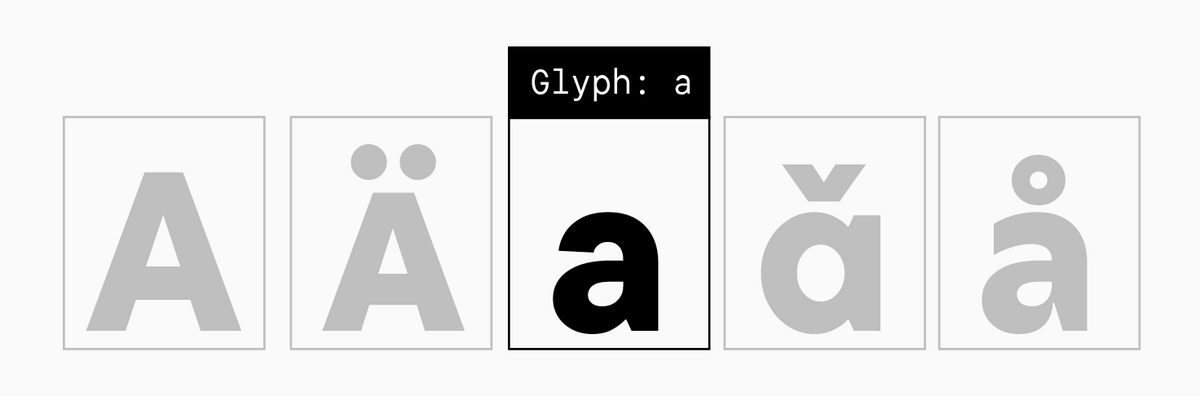
Словарь типографических терминов
Шрифтовой словарь TypeType — это справочник, в котором вы найдете определения типографических терминов, использующихся в наших статьях и других материалах о шрифтах. Изучение языка типографики поможет вам глубже понимать специализированные источники информации и быть со шрифтами на «ты», эффективно применяя их в своих дизайн-проектах.
Напомним, что общепринятой терминологии на шрифтовом рынке не существует — здесь мы приводим определения, основанные на многолетнем опыте специалистов TypeType: по нашему мнению они наиболее точные.
Акцидентные шрифты
Display fonts
(дисплейные шрифты) - яркие характерные шрифты, привлекающие внимание, обычно используются в крупных размерах (заголовках).
Антиква
Antiqua (serif typeface)
Контрастный шрифт с засечками.
Апекс, вершина
Apex
Место соединения двух штрихов (наклонных или наклонного и вертикального) в верхней части некоторых букв ("А", "М").
Апертура
Aperture
Это степень открытости знака. Апертура бывает закрытой и открытой. Понять, что такое апертура, проще всего на примере буквы ''С'': более загнутые / стремящиеся к вертикали — закрытая апертура; более прямые / горизонтальные терминалы — открытая апертура.
Апрош
Letterspace (aprosh)
См. "Полуапрош".
Арка
Arc
Дуга "стоящая" на двух стемах.
Базовая латиница
Basic Latin
Блок юникода, включающий в себя "базовые" знаки языков, основанных на латинской традиции письма.
Базовая линия
Baseline
Линия, на которой "стоят" знаки шрифта: она проходит по нижнему краю знаков без учета свисаний и нижних выносных элементов.
Вертекс, вершина
Vertex
Место соединения двух штрихов (наклонных или наклонного и вертикального) в нижней части некоторых букв (например, в букве "V", "W").
Вертикальная засечка
Vertical serif
Засечка, завершающая горизонтальные элементы таких знаков, как "Е" или "Т", и дуги таких знаков, как "С", "S" и т. д. В некоторых шрифтах в строчных знаках вертикальная засечка модифицируется в каплю в таких знаках, как "a" или "c".
Верхний выносной элемент
Ascender
Элемент в строчных буквах, выходящий за Х–Hight.
Ветка
Branch
См. "Рука", "Нога".
Влитие
Junction
Место плавного присоединения полуовала к стему.
Внутрибуквенный просвет
Counter
Внутренняя "пустая" часть знака, область белого внутри знака.
Восходящий штрих
Upstroke
Диагональный штрих, который идет снизу вверх (например, левый штрих буквы "А").
Гарнитура
Typeface
(шрифтовое семейство) - комплект шрифтов, связанных определенными характеристиками (стилистическими или техническими). Частью одной гарнитуры могут быть шрифты разных стилей, и начертаний (прямые, курсивные, светлые, насыщенные и т.д).
Геометрические гротески
Geometric sans serif typefaces
Шрифты, намеренно построенные на простейших геометрических формах (равносторонний треугольник, квадрат, круг). Появились в Германии в 30-е годы ХХ века. Влияние на их появление оказали идеи конструктивизма и школы дизайна Баухауз.
Глаз
Eye
Внутренняя замкнутая часть строчной буквы "e".
Глиф
Glyph
Принятый в типографике и дизайне профессиональный термин, который обозначает конкретное графическое изображение знака (буквы, цифры, символа) в рамках одного шрифта.
Графема
Grapheme
Это сама идея знака, его образ и базовая форма, позволяющая отличать его от других знаков. У одного знака может быть несколько графем (например, прописные или строчные, прямые или курсивные, одночастные или двухчастные буквы).
Гротеск
Grotesque (sans serif typeface)
Неконтрастный или малоконтрастный шрифт без засечек.
Гуманистические гротески
Humanist sans serif typefaces
Это гротески, которые отличаются от других гротесков более заметным присутствием контраста толстых и тонких штрихов. У них открытые апертуры, а знаки "а" и "g" чаще всего имеют двухчастную форму.
Двухчастная форма
Double-storey form
Традиционная форма букв "a" и "g", конструкция которых состоит из двух частей — "верхней" и "нижней".
Деноминаторы
Denominators
Уменьшенные формы маюскульных цифр, используются в качестве знаменателя.
Диакритические знаки
Diacritical marks
Специальные знаки, расположенные над или под литерами (иногда — внутри), которые влияют на значение буквы — меняют его или уточняют. Например, в русском языке диакритическими знаками является диерезис над "ё" и бреве над "й".
Динамические шрифты
Dynamic fonts
Отличаются заметной динамикой пропорций, наличием контраста и открытой апертурой.
Дополнительный штрих
Additional stroke
Штрих, не являющийся основным или соединительным (например, горизонтальные элементы "Е").
Дуга
Bowl (1)
Часть окружности или округлого элемента знака
Засечка
Serif
Короткие дополнительные штрихи на конце основных штрихов знака, обычно перпендикулярные им. Наличие засечек характерно для антикв и брусковых шрифтов (slab serif).
Инстансы
Instances
Начертания, которые не были отрисованы в качестве мастеров. Они интерполируются или экстраполируются между опорными начертаниями исходя из специальных формул расчëта толщин шрифтового семейства.
Интерполяция
Interpolation
Автоматическое (математическое) генерирование промежуточных форм из двух крайних версий. Например, применительно к разработке шрифтов: при наличии мастеров Regular и Bold генерация (интерполяция) инстанса Demibold (см. "Инстансы").
Инфериоры
Inferiors
Уменьшенные формы маюскульных цифр, используются в различных формулах и математических выражениях.
Италики
Italics (true italics)
(тру италики или настоящие италики) - исторически так обозначали курсивные шрифты, сегодня термин используется в более широком смысле и объединяет тру италики и наклонные шрифты. Это наклонные шрифты, где графемы строчных знаков меняются на курсивную форму. Могут создаваться как отдельный полноценный шрифт, а не как дополнение к прямому начертанию. В основном характерны для шрифтов с засечками.
Каллиграфия
Calligraphy
Искусство художественного письма. Каллиграфический текст создается вручную и всегда несет в себе след пишущего инструмента.
Капитель
Small caps
Это формы знаков, которые имеют графику прописных букв, но уменьшены по высоте и скомпенсированы по весу. В основном рисуются немного выше строчных знаков, но в латинской традиции капитель может быть в рост строчных. Используются в аббревиатурах или в других ситуациях, где требуется сплошной набор прописными буквами.
Капля
Drop
Модифицированная вертикальная засечка на конце дуги. Форма менее очерченная и геометричная в старостильных антиквах, в новостильных очертанием напоминает круг или каплю.
Кассовый состав
Character set
Совокупность всех знаков, входящих в шрифт.
Кегельная площадка
Em-space
В металлическом наборе это плоскость литеры, на которой расположен знак. Кегельная площадка в цифровом шрифте — это прямоугольник, в котором расположен контур знака. Сделать кегельную площадку шире или уже в цифровом шрифте можно увеличивая или уменьшая полуапроши глифа.
Кегль
Point size
Высота символов шрифта, то есть размер по вертикали. Измеряется в типографских пунктах.
Кернинг
Kerning
Технический термин, обозначающий избирательное увеличение или уменьшение интервала между двумя символами, обусловленное сочетанием их форм. Делается для создания максимально ровного набора.
Клюшка
Hockey stick
Левый штрих буквы "Л", включая терминал.
Кодировка
Encoding
Упорядоченный комплект знаков шрифта. Проще говоря, это система, определяющая, как символы представлены в памяти устройства и как они отображаются на экране. У каждого символа в кодировке есть уникальный номер — кодовая точка. Кодировка зависит от операционной системы, для которой предназначен шрифт. Существует множество различных кодировок, одна из самых распространенных — Unicode.
Контраст
Contrast
Соотношение толщин основных и дополнительных штрихов в шрифте. Так, шрифт может быть неконтрастным, малоконтрастным, контрастным и сверхконтрастным.
Контрформа
Counterform
См. "Внутрибуквенный просвет".
Концевые элементы
Stroke ending
См. "Терминал".
Кривые Безье
Bézier curve
Математически описанные кривые, которые применяются для описания форм знаков в цифровых шрифтах.
Круглые, прямоугольные и треугольные знаки
Rounded, rectangular, and triangular characters
Условное разделения знаков на группы, основанное на их формах., Прямоугольные знаки — "Н", "П", "F", круглые — "O", "С", треугольные и знаки с диагоналями — "А", "К", "Y" и т. п.
Ленточная антиква
Сontrast sans
Антиква без засечек с ярко выраженным контрастом.
Леттеринг
Lettering
Это нарисованная вручную надпись, или рисованный алфавит, который впоследствии не собирается в шрифтовой файл. Леттеринг может быть как на основе каллиграфии, так и на основе шрифта или вообще иметь под собой свою логическую систему построения.
Лигатура
Ligature
(от лат. ligare — связывать) — это знак (символ), образованный путем соединения двух или более букв. Изначальная задача — создавать гармоничную конфигурацию букв, которые не в лигатуре пересекаются (например, fi). Сегодня лигатуры часто используются для декоративных целей.
Литера
Letter- Брусок с выпуклым знаком на одной плоскости формы, обычно выполненный из гарта или дерева, позволяющий переносить знак на поверхность путем оттиска (печатать);
- В широком смысле — любая буква или знак шрифта, или элемент шрифта.
Ловушка для чернил
Ink Trap
Специфический вариант оптической компенсации набора. Достигается за счёт дополнительного углубления на вершинах острых углов внутрибуквенного пространства. Изначально добавление ловушек требовали условия печати. В острых углах краска могла затекать и нарушать баланс набора. Ловушки принимали на себя излишек краски и уменьшали эту проблему. Качество печати возросло, но добавление ловушек остаётся актуальным в частности для мелкого кегля. В современных шрифтах ловушки для краски в стали не столько технической необходимостью, сколько графическим ходом и высказыванием.
Логика пера
Pen logic
Основа для понимания правил построения шрифтов и их классификации. Набор правил письма различных исторических почерков, включающих в себя понятия об угле наклона, контрасте, и движениях пера (остроконечного или ширококонечного).
Мастера
Masters
Опорные начертания, которые шрифтовой дизайнер отрисовывает вручную в шрифтовых редакторах, поддерживающих технологию вариативности.
Мастеринг
Mastering
Принятый в шрифтовом дизайне профессиональный термин, обозначающий технический и программный этапы подготовки шрифта к выпуску.
Маюскульные цифры
Lining (majuscule) figures
Цифры без верхних и нижних выносных элементов, рост которых приближен или равен росту прописных знаков. Чаще всего присутствуют в шрифтах по умолчанию.
Метрики
Metrics
Технические характеристики, описывающие спейсинг, керниг и другие параметры знаков, встроенные в файл шрифта.
Минускульные цифры
Old-style (minuscule) figures
Цифры с верхними и нижними выносными элементами, рост которых приближен к строчным знакам. Иногда называются текстовыми, т. к. традиционно они используются именно в наборе, что делает его приятнее для читателя. Обычно рисуются в шрифте как дополнительный комплект цифр и включаются с помощью фичи Oldstyle Figures.
Моноширинные засечки
Monospaced serifs
Экстремально широкие засечки, компенсирующие ширину кегельной площадки для узких знаков в моноширинных шрифтах. Характерны для знаков "i", "l", "I", "1".
Моноширинные шрифты
Monospaced fonts
Это шрифты, у которых одинаковая ширина кегельных площадок во всех знаках. Традиционно такие шрифты используются для программирования и заполнения таблиц, но также применяются в современной типографике.
Наборный шрифт
Шрифт, которым набирается текст при помощи печатного станка или компьютера. Наборный шрифт может быть как текстовым, так и акцидентным.
Наклонные шрифты
Oblique fonts
Шрифты, которые обычно рисуются в пару к оригинальному прямому начертанию. При этом графемы знаков не меняются, а лишь приобретают наклон. В основном характерны для гротесков.
Наплыв
Stress
Область максимального утолщения дуги в круглых знаках и округлых элементах.
Насыщенность
Weight
Толщина элементов знаков по отношению к высоте. Шрифты бывают не насыщенные или светлые (например, начертания Thin или Light) и насыщенные или тёмные/жирные (например, начертания Bold или Black).
Начертание
Style
Внешний вид шрифта. В рамках одного начертания все знаки шрифта будут выполнены в едином весе, ширине или, например, будут наклонными. Так, в подсемейство могут входить шрифты разных начертаний, объединенных по одному признаку. А в гарнитуре в свою очередь объединяются различные подсемейства.
Неогротески
Neo-Grotesques
Это наследие швейцарского дизайна. Отличительные особенности этих шрифтов — равноширинные пропорции знаков, малозаметный или отсутствующий контраст, сквадраченные овалы, закрытые апертуры.
Нижний выносной элемент
Descender
Элемент буквы или знака, расположенный под базовой линией (выступающий за ее пределы).
Нисходящий штрих
Downstroke
Диагональный штрих, который идет сверху вниз (например, правый штрих буквы "А").
Новостильная антиква
Modern (Classical) serif typefaces
(или классицистическая антиква) — класс равноширинных шрифтов, которые носят глиптальный характер, то есть в основе их рисунка лежит построение, а не почерк. Подобный вид шрифтов развился благодаря широкому применению остроконечного пера и технике гравировки на металле. Характеризуются высоким контрастом, тонкими и симметричными засечками, отсутствием динамики, прямой осью овалов.
Нога
Leg
Нижние диагональные штрихи в таких буквах как K, R, Я, Ж.
Нумераторы
Numerators
Уменьшенные формы маюскульных цифр, используются в качестве числителя.
ОpenType фичи
OpenType features (or simply features)
(или просто фичи) — код, который прописывается при разработке шрифта, чтобы пользователь мог вызвать те или иные изменения и применять функции (предусмотренные шрифтовым дизайнером), используя шрифт в графическом редакторе. Например, заменить формы знаков на альтернативные, включить табулярные или минускульные цифры, изменить уровень посадки пунктуации в зависимости от регистра.
Овал
Oval
Замкнутый элемент знаков или частей знаков, образующий круг или эллипс.
Одночастная форма
Single-storey form
Упрощённая форма букв "a" и "g", возникшая в геометрических гротесках и основанная на форме круга.
Оптические компенсации
Visual compensations
Графические приемы, применяющиеся для исправления нежелательных эффектов, которые могут появиться в шрифте при использовании в определённых условиях (например, при печати или при использовании в мелком кегле). Одна из распространённых методик — утоньшение некоторых элементов знаков в жирных начертаниях.
Ось наклона овала
Axis
Воображаемая ось, которую можно провести через наиболее тонкие участки в округлых знаках. Угол наклона определяется относительно вертикали. Он обусловлен традициями распределения контраста исходя из движения пишущего инструмента.
Перекладина, бар
Cross(bar)
Горизонтальный, не основной, штрих.
Переходная антиква
Transitional serif typefaces
Получила своё название потому, что исторически и графически эти шрифты находятся между старостильной и новостильной антиквой. Принято считать, что переходная антиква появились в середине XVIII века. Визуально переходные антиквы более утонченные, контрастные и "рисованные", чем старостильные.
Петля
Loop
Замкнутый выносной элемент в букве "g".
Пламевидный элемент
Branch
Выносной элемент строчной буквы "б".
Плечо
Shoulder
Cм "Арка".
Подсемейство
Subfamily
Набор шрифтов внутри гарнитуры, объединенных по стилистическому признаку (наклону, насыщенности, весу и так далее).
Полуапрош
Letterspace (aprosh)
Расстояние от знака до края кегельной площадки. Может быть как положительным, так и отрицательным. Два полуапроша рядом стоящих знаков образуют апрош.
Полуовал
Bowl
Округлая часть знака, которая не образует полную окружность. Может быть разомкнутый (например, в "З") или примыкать к стему (например, в "B").
Прописные
Uppercase
(заглавные) — "большие" буквы шрифта. Прописные буквы используются в начале первых слов предложений, в начале имен собственных, географических названий и т. п.
Пропорции знаков
Character proportions
Соотношение между шириной и высотой знака.
Пункт типографский
Point
Единица измерения кегля шрифта, основная единица типометрической системы. Пункт равен приблизительно 1/72 части дюйма. В разных системах счисления (например, американской и французской) эти значения немного отличаются.
Равноширинные шрифты
Fonts with static proportions
Это такие шрифты, знаки которых визуально стремятся к схожей ширине, за исключением самых узких (таких как ''i'' и ''l'').
Разноширинные шрифты
Fonts with dynamic proportions
Шрифты с явной динамикой ширин. Их пропорции отсылают к римскому монументальному шрифту или антиквам эпохи Возрождения.
Растр
Raster
Массив пикселей (точек краски), с помощью которых воспроизводится изображение на устройствах вывода.
Расширенная латиница
Extended Latin
Блоки юникода, включающие в себя знаки языков, основанных на латинской традиции, которые не входят в блок базовой латиницы.
Рисованный шрифт
Handwritten font
Это шрифт, нарисованный вручную, при этом визуально похожий на наборный (чаще, титульный шрифт). Используется для оформления книг, плакатов и так далее. Более узкое понятие, чем леттеринг.
Ритм шрифта
Rhythm
Формируется за счёт межбуквенных расстояний, внутрибуквенных просветов и зависит от рисунка самих букв (в первую очередь стемов), их направления и симметричности.
Рука
Arm
Штрих, направленный вверх по диагонали.
Свисание
Overhang
Выступ контура круглого или остроконечного знака за базовую линию или линию роста строчных/прописных знаков, сделанный в целях оптической компенсации знаков. Без свисаний знаки будут казаться меньше эталонных букв "Нн" и других прямых форм.
Свисающий элемент
Descending element
«Ножки» кириллических букв "Дд", "Щщ", "Цц".
Скрипт
Script
Cм "Рисованный шрифт".
Слаб, брусковый шрифт
Slab, slab serif
Шрифт с массивными засечками. Отличается от обычных антикв слабо выраженным контрастом или его полным отсутствием.
Соединение без шпоры
Spurless junction
Противоположность соединения со шторой, встречается в некоторых форм букв "G" и "b".
Соединительный штрих
Connecting stroke
Дополнительный штрих, соединяющий основные. Может быть горизонтальным или наклонным.
Спейсинг
Spacing
Технический термин, обозначающий расстояние между всеми знаками в тексте. Объединяет в себе все расстояния между символами в шрифте: настройки апрошей и кернинга. Спейсинг может быть более плотный или разряженный.
Спинка
Spine
Центральный изогнутый штрих у латинской буквы "s" и производных от неё знаков.
Средняя линия, талия
Waist
Воображаемая линия, проходящая через оптический центр знака. Она может быть завышенной или заниженной в зависимости от вида и стиля шрифта.
Старостильная антиква
Old Style (Humanist) serif typefaces
(или гуманистическая антиква) - так называют антиквы, которые появились и активно развивались в эпоху Возрождения. Это динамические шрифты с невысоким контрастом, большим наклоном оси овалов, несимметричными округлыми засечками. Этот класс шрифтов относится к дуктальным, они основаны на логике письма ширококонечным пером. Старостильные антиквы характеризуются малым контрастом штрихов, и скругленными засечками.
Старые гротески
Old sans serifs
К этому классу относятся первые гротески, появляющиеся с XIX века. Шрифты имеют заметный контраст, простые формы, знаки стремятся к равноширинности.
Статические шрифты
Static fonts
Пропорции знаков в таких шрифтах обычно уже, чем в динамических. Знаки визуально стремятся к схожей ширине, апертура закрытая.
Стем
Stem
Основной доминирующий вертикальный (или наклонный) штрих.
Стилистические альтернативы
Stylistic alternates
Знаки альтернативных форм, заложенные в гарнитуру. Например, в базовом наборе знаков шрифта может быть двухчастная "а", а среди стилистических альтернатив — одночастная. Включить альтернативные знаки в наборе можно через ОТ-фичи.
Стиль
Style
См. "Начертание".
Строчные
Lowercase
"Маленькие" буквы шрифта. Используются для набора основного текста.
Супериоры
Superiors
Уменьшенные формы маюскульных цифр, используются для сносок и математических выражений.
Табулярные цифры
Tabular figures
Набор цифр с одинаковой шириной кегельной площадки (можно назвать их моноширинными). Созданы для удобного заполнения таблиц. Бывают в разных регистрах.
Текстовые шрифты
Text typefaces
Спокойные нейтральные шрифты без лишних деталей, которые удобно читаются и подходят для набора больших объемов текста.
Терминал
Terminal
Прямое или изогнутое окончание штриха.
Тестовые слова
Test words
Несуществующие слова НОБЕЛЬФАЙК (или КИБЕРНОСУФА) и HANDGLOVES, которые шрифтовые дизайнеры традиционно используют в начале работы над шрифтом, т. к. в этих словах собрано большинство стилеобразующих элементов шрифта.
Ухо
Ear
Элемент, расположенный справа сверху у строчной двухчастной "g".
Флаг
Flag
Верхняя горизонтальная черта в цифре 5 или горизонтальный элемент в курсивных формах "v", "w".
Формула Pablo Impallari
Pablo Impallari formula
Одна из наиболее распространённых формул для расчёта толщин стемов для шрифтового семейства.
Х–height
Заданный параметр высоты строчных букв внутри одного шрифта; линия роста строчных знаков без учёта свисаний.
Хвост
Tail
Выносной изогнутый штрих у некоторых букв (например, "Q" или "у").
Хинтинг
Hinting
Технический термин, обозначающий процесс оптимизации шрифтов формата TrueType или PostScript для достижения максимальной читаемости на экране компьютера.
Подробнее о хинтинге.
Чаша
Bowl (2)
Нижняя дуга таких букв, как "Ч", "U", "u".
Шпора, шип
Spur
Небольшой "отросток", который образует часть стэма в месте влития, например, в некоторых формах букв "G", "d".
Шрифт
Font
Набор символов, объединенных общим характером — это и сам рисунок знаков (буквы, цифры, знаки препинания), объединённых общей системой, и файл, несущий в себе полный набор литер — алфавитных и/или не алфавитных знаков — используемых для набора.
Шрифтовая пара
Font pair
Это сочетание двух дополняющих друг друга шрифтов в одном макете. Чаще всего в такой паре один из шрифтов играет роль заголовочного и создаёт необходимую интонацию, а второй служит для передачи информации.
Шрифтовой редактор
Font editor
Программное обеспечение, позволяющее создавать и редактировать цифровые шрифты.
Экстраполяция
Extrapolation
Автоматическое (математическое) генерирование форм, выходящих за пределы двух крайних версий. Например, применительно к разработке шрифтов: при наличии мастеров Regular и Bold генерация (экстраполяция) инстанса Thin. См. также Интерполяция.
Экстремумы
Extreme points
Крайние точки на вертикальной и горизонтальной оси округлых элементов, из которых строится дуга.
Юникод
Unicode
Международный стандарт кодирования символов, включающий знаки большинства языков мира, в том числе небуквенные символы. Каждому символу присвоено своё числовое значение.